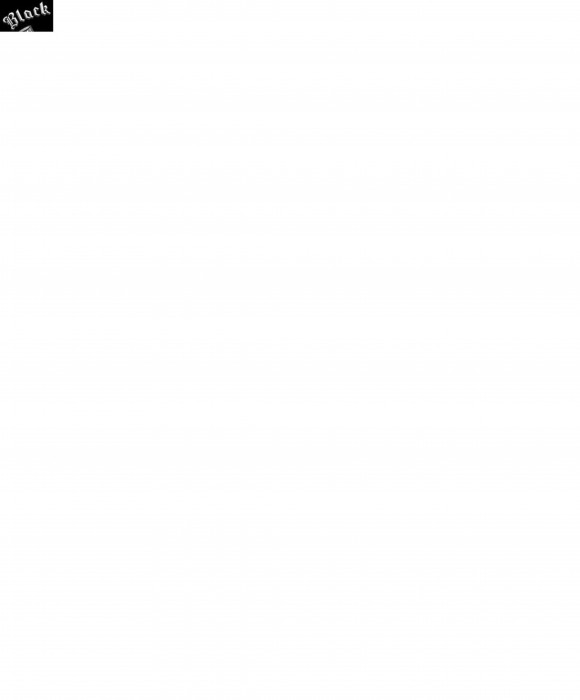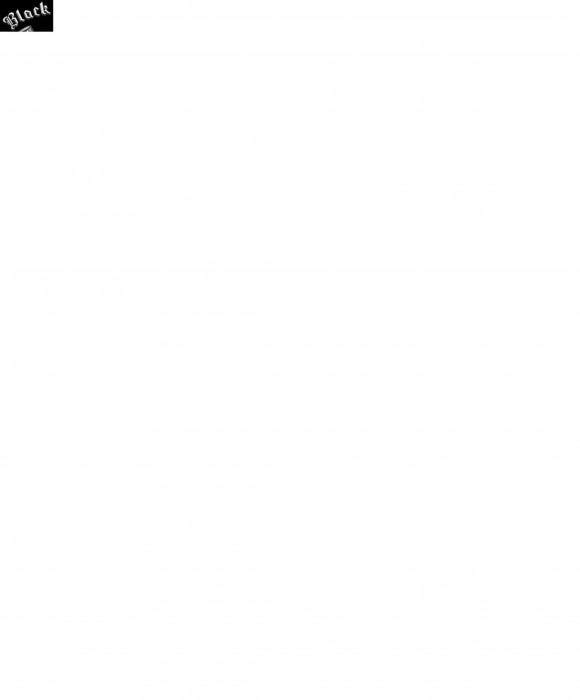
Wer kennt diese schriftart
Eine Bitte: Wenn du hier schon so ein winziges Schriftmuster einstellst, dann doch bitte nicht mit einem m² weißer Fläche unten dran.
Sonst schau dich mal bein "Rekordhalter" der Frakturschriften in seinem Katalog um,da ist mit Garantie etwas für dich passendes dabei:
Bei dem winzigen "Black" Schnippelchen ist das auch verdammt schwer. Ist das gestickt?
Schaut, soweit man das zwischen den Pixeln erkennen kann, ein wenig so aus. Ich titppe auf irgend eine, für ein Maschinen-Stickprogramm vereinfachte Gotisch.